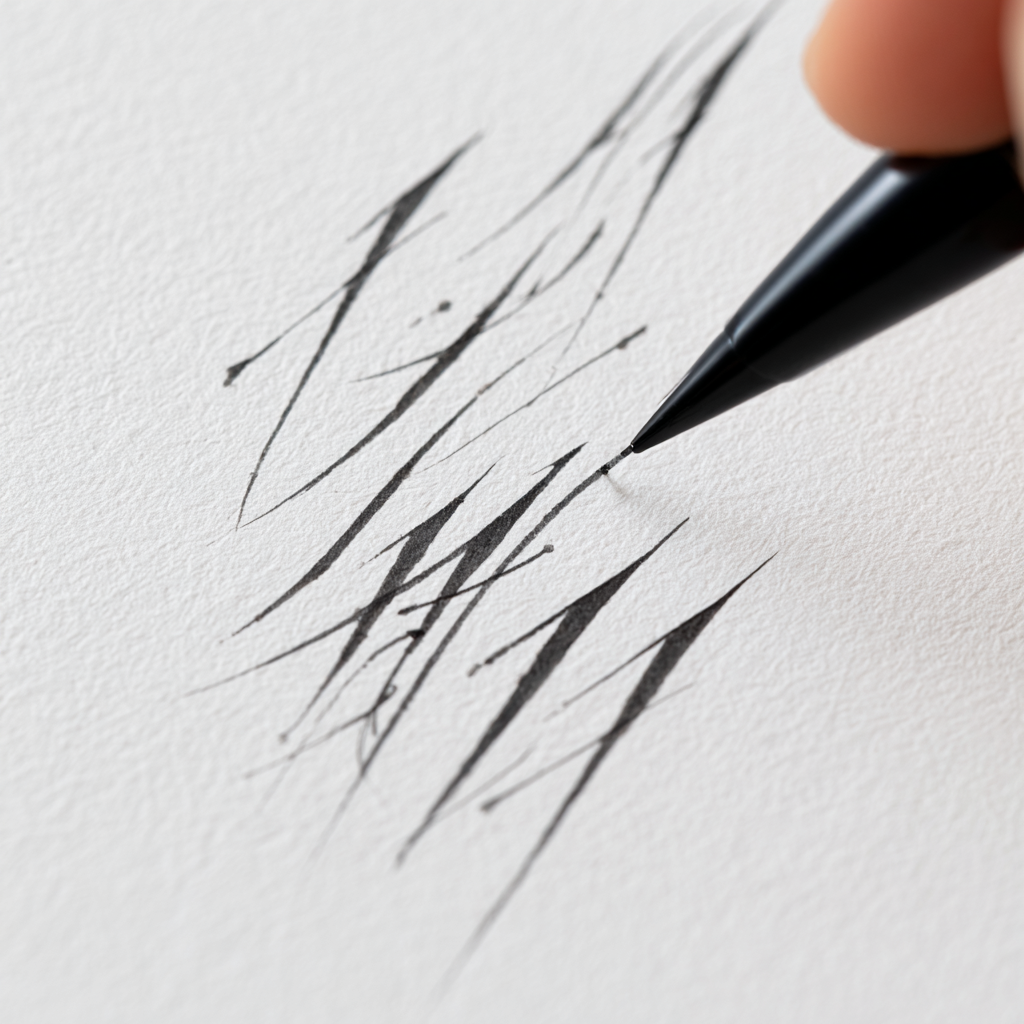
✍ 손글씨에 콤플렉스를 가지고 있었던 시절, 글씨만 보면 움츠러들곤 했어요. 누구보다도 마음을 담아 쓰고 싶은데, 나의 손글씨는 언제나 삐뚤빼뚤하고 정돈되지 않았죠. 그래서 늘 글씨 쓰는 순간이 두려웠어요.
하지만 어느 날 우연히 접한 캘리그라피는 저에게 새로운 가능성을 열어줬어요. 예쁜 글씨가 아니라 '느낌 있는 글씨'라는 문구가 얼마나 위안이 되었는지 몰라요. 글씨에 감정을 담을 수 있다는 사실은 정말 놀라웠죠.
지금부터는 제가 어떻게 콤플렉스를 극복하고, 손글씨를 통해 더 당당해질 수 있었는지 그 과정을 자세히 이야기해볼게요! 😊
🖋 손글씨 콤플렉스의 시작
어릴 적부터 글씨체에 대해 자주 지적을 받았던 기억이 있어요. 선생님들은 깔끔하게 쓰라고 했고, 친구들은 장난스럽게 제 글씨를 흉내 내기도 했죠. 이런 상황들이 반복되다 보니, 어느새 '내 글씨는 못생겼다'는 생각이 뿌리처럼 자리를 잡게 되었어요.
학교 시험지나 친구 생일 카드처럼 글씨를 써야 하는 순간마다 긴장이 되었고, 누군가 내 글씨를 읽을까 봐 불안했어요. 그래서 글씨를 작게 쓰거나 대충 흘려 쓰는 습관이 생겼고, 그럴수록 더 지적을 받게 되는 악순환이 반복됐죠.
내가 생각했을 때 글씨라는 건 단순히 정보를 전달하는 수단이 아니라, 나 자신을 보여주는 방식 중 하나였어요. 그래서 더더욱 글씨에 자신감이 없다는 게 자존감에도 영향을 주더라고요.
이런 콤플렉스를 안고 사회생활을 시작하면서는 메모나 회의록 작성할 때조차 불안해졌고, 디지털 입력에만 의존하게 됐어요. 하지만 어느 날, 예쁜 손글씨로 쓰인 메모 한 장이 제게 깊은 인상을 남기게 되었어요.
📝 콤플렉스를 느끼는 주요 상황 정리
상황 느낌 결과 시험지 작성 글씨체 때문에 점수에 영향 갈까 걱정 불안감 증가 친구에게 카드 작성 내 글씨가 부끄러워 망설임 프린트로 대체 회사에서 회의 메모 글씨를 보는 동료 눈치 보임 자신감 저하 이런 반복된 경험 속에서 나는 내 글씨를 '고칠 수 없는 것'이라 여기게 되었지만, 사실은 마음을 들여다보는 시간과 노력이 필요했던 거였어요. 그런 전환점이 바로 캘리그라피였답니다! ✨
💭 왜 콤플렉스가 되었을까?
손글씨에 대한 콤플렉스는 단순히 ‘글씨가 예쁘지 않다’는 데서 끝나지 않았어요. 사회적으로는 정돈된 글씨를 성실함이나 성격과 연결짓는 경우가 많았거든요. 마치 글씨체가 곧 성격의 반영이라는 인식이 부담으로 작용했죠.
특히 ‘글씨 예쁘다’는 말이 칭찬으로 여겨지는 문화 속에서, 그 반대에 서 있는 사람들은 자연스럽게 위축되곤 해요. 제 글씨는 칭찬을 듣기보다는 “잘 안 보인다”, “조금 알아보기 힘들다”는 말을 자주 들었거든요.
그때부터 저는 누가 옆에서 내 글씨를 보는 상황을 피하려고 했어요. 회의 메모를 직접 공유하기보다는 메일로 타이핑해서 보내는 쪽을 선호하게 되었고, 종이에 뭔가를 쓰는 일을 점점 꺼리게 되었어요.
이런 내면의 불안은 자신감 결여로 이어졌어요. 글씨가 예쁘지 않다고 해서 내가 못난 건 아니지만, 사회적 시선이 글씨로 사람을 평가하는 경우가 많다는 걸 느끼며 무의식적으로 나를 낮추게 된 거죠.
🌿 캘리그라피와의 첫 만남
우연히 SNS에서 봤던 짧은 문구 하나가 마음을 움직였어요. “예쁜 글씨가 아니라 느낌 있는 글씨가 되자.” 그 말은 마치 나에게 하는 말처럼 느껴졌어요. 그렇게 저는 캘리그라피를 배우기로 마음먹었답니다.
처음 시작할 땐 도구 하나하나가 낯설었어요. 붓펜, 먹물, 워터브러시… 단순한 볼펜과는 다른 감각이 필요했죠. 하지만 글씨를 쓸수록 '표현'이라는 단어가 떠올랐어요. 나의 감정을 글씨에 담아내는 것, 그게 바로 캘리그라피였어요.
처음엔 ‘나도 잘할 수 있을까?’ 하는 걱정이 컸지만, 연습장을 채워가는 과정 속에서 스스로의 글씨에 감정이 묻어나는 걸 느끼게 되었어요. 그게 참 신기했고, 더 연습하고 싶어졌어요.
무엇보다 캘리그라피는 '틀림'이 아니라 '다름'을 인정하는 예술이었어요. 글씨가 삐뚤하다고 해도, 그 자체로 멋있을 수 있다는 걸 배우면서 나 자신을 조금씩 받아들이게 되었죠.
🎨 캘리그라피 초보자 필수 도구 리스트
도구 용도 추천 이유 붓펜 자유로운 획 표현 붓처럼 느낌 살림 워터브러시 색상 번짐 표현 감성적인 분위기 먹물 전통적 느낌 강조 묵직한 표현 가능 처음엔 서툴고 느렸지만, 글씨를 쓴다는 행위가 점점 즐거워졌어요. 도구를 고르는 것도 하나의 재미였고, '내가 이렇게 집중할 수 있었나?' 싶을 정도로 몰입하게 되었죠.
🖌 꾸준한 연습이 가져온 변화
매일 10분씩이라도 손을 움직이기로 마음먹었어요. 처음엔 ‘ㄱㄴㄷ’부터 시작했지만, 어느 순간 문장을 써보고 싶더라고요. 짧은 시구나 명언을 따라 쓰면서 감정이 깃든 글씨를 배우는 데 재미를 느꼈어요.
글씨가 갑자기 예뻐지진 않았지만, 느낌이 생겼어요. 나만의 획, 나만의 흐름이 생기니까 글씨에 자신감도 붙기 시작했죠. “너무 멋지다!”는 아니더라도 “느낌 있어!”라는 말을 들을 때마다 뿌듯했어요.
이전에는 글씨 쓸 일이 있으면 피했지만, 이제는 일부러 손글씨로 편지를 쓰기도 해요. 누군가에게 내 글씨로 감정을 전달할 수 있다는 것 자체가 감격스러웠죠. 디지털 시대에 손글씨는 더 진심처럼 느껴졌거든요.
계속 쓰다 보니 캘리그라피가 단순한 글씨가 아니라 하나의 ‘작품’이라는 생각이 들었어요. 그래서 전시회나 클래스도 다니며 더 많은 사람들과 소통하게 되었고, 글씨로 사람과 연결된다는 기쁨도 알게 되었죠.
💓 감정과 글씨가 연결될 때
글씨는 그날의 기분을 그대로 반영하더라고요. 기분이 좋을 땐 획이 부드럽고 여유 있게 나오고, 스트레스를 받을 땐 강하게 눌러 쓰게 되었죠. 그걸 의식하기 시작하면서 글씨가 내 감정의 일기장이 되기 시작했어요.
어느 날은 우울한 마음에 먹물을 가득 묻혀 눌러썼던 글씨가 마음을 정화해줬고, 기쁜 날은 밝은 색 워터브러시로 경쾌하게 적어내리며 스스로를 칭찬하기도 했어요. 이렇게 감정을 표현할 수 있는 통로가 생긴 건 정말 소중한 일이에요.
캘리그라피는 글씨를 예쁘게 쓰는 게 목적이 아니라, 나를 표현하고 감정을 정리하는 하나의 방법이 되어줬어요. 내 마음을 이해하는 도구로써 글씨를 다시 보게 되었죠.
이제는 매일 쓰는 글씨가 누군가에게 위로가 되기도 하고, 나 스스로를 치유하는 수단이 되기도 해요. 손글씨로 시작한 여정이 이렇게 감정의 치유로 이어질 줄은 정말 몰랐어요.
🌈 지금은 어떻게 달라졌을까?
지금은 손글씨에 대한 콤플렉스가 거의 사라졌어요. 완벽하진 않지만, 나만의 감성이 담긴 글씨를 자신 있게 쓸 수 있게 되었거든요. 주변에서도 “글씨에 너의 감정이 보여서 좋아”라는 말을 자주 해줘요.
손글씨를 통해 저를 더 많이 이해하게 되었고, 감정 표현도 훨씬 자연스러워졌어요. 지금은 매일 글씨를 쓰는 시간을 소중히 여기고, 작지만 진심이 담긴 엽서 한 장을 친구들에게 자주 보내곤 해요.
캘리그라피는 단순히 콤플렉스를 극복하는 수단이 아니라, 저 자신을 알아가는 여정이 되어줬어요. 요즘은 내 글씨로 문장 하나를 완성할 때마다 성취감을 느껴요. 그건 타인이 줄 수 없는 감정이랍니다.
글씨로 내 감정을 전하고, 그게 누군가의 마음을 움직일 수 있다는 건 참 놀라운 일이에요. 손글씨를 부끄러워하던 사람이 이렇게 변화할 수 있다는 걸 보여주고 싶어요! 😊
📚 FAQ
Q1. 글씨 콤플렉스는 정말 고칠 수 있나요?
A1. 네, 연습과 감정 표현을 통해 충분히 극복할 수 있어요. 중요한 건 완벽함이 아니라 ‘표현’이라는 걸 기억하세요!
Q2. 캘리그라피 시작하려면 어떤 도구가 필요하죠?
A2. 붓펜 하나면 시작할 수 있어요. 점차 워터브러시, 먹물 등 자신에게 맞는 도구를 찾아보세요.
Q3. 매일 얼마나 연습하면 효과가 있을까요?
A3. 하루 10분씩만 꾸준히 해도 놀라운 변화가 생겨요. 중요한 건 ‘지속성’이에요.
Q4. 글씨체가 예쁘지 않아도 캘리그라피 할 수 있나요?
A4. 물론이죠! 오히려 개성 있는 글씨가 더 매력적일 수 있어요.
Q5. 캘리그라피를 독학해도 괜찮나요?
A5. 유튜브나 책으로도 충분히 배울 수 있어요. 요즘은 온라인 클래스도 많답니다!
Q6. 손글씨 연습장 추천해 주세요.
A6. 격자형 연습장이나 무지노트가 좋아요. 종이 질감이 너무 미끄럽지 않은 것이 좋아요.
Q7. 글씨를 예쁘게 쓰는 팁이 있나요?
A7. 천천히 쓰는 습관을 들이는 게 가장 좋아요. 속도가 느릴수록 획이 안정돼요.
Q8. 감정을 담는 글씨는 어떻게 표현하나요?
A8. 문장 내용에 맞는 색감이나 획의 굵기를 바꾸면 감정이 더 잘 전달돼요. 자연스럽게 자신만의 스타일이 생긴답니다.